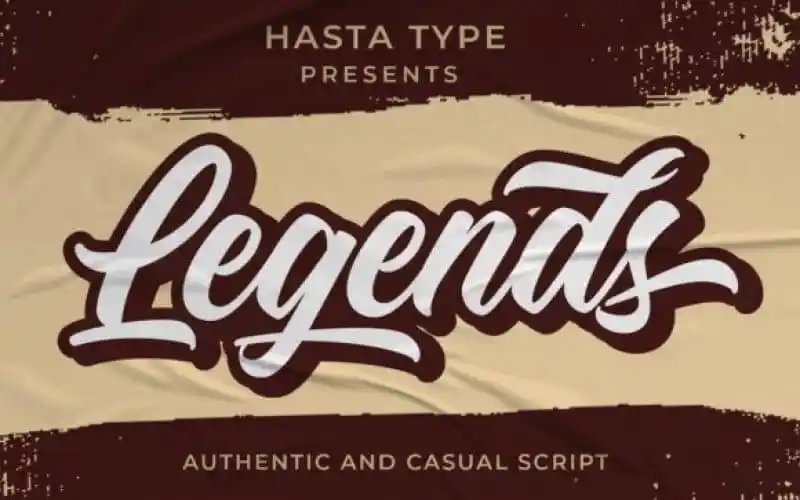
Legends Calligraphy Font
Descubra a magia da Legends Calligraphy Font, uma elegante fonte à mão escrita que se destaca por sua simplicidade e amabilidade. Esta fonte apresenta um estilo robusto e suave, oferecendo inúmeras possibilidades para expressar suas ideias criativas de maneira única. Criada e compartilhada pelo IklazStudio, Legends Calligraphy é perfeito para logos, embalagens de produtos, identidade visual e muito mais. Seu design autêntico em PUA (Unicode) permite que você facilmente acesse todos os caracteres e desenhos especiais desta fonte. Não hesite em explorar as possibilidades criativas com Legends Calligraphy Font – ela é uma escolha ideal para designers buscando expressar sua visão de maneira única e sofisticada, seja em projetos digitais ou impressos.